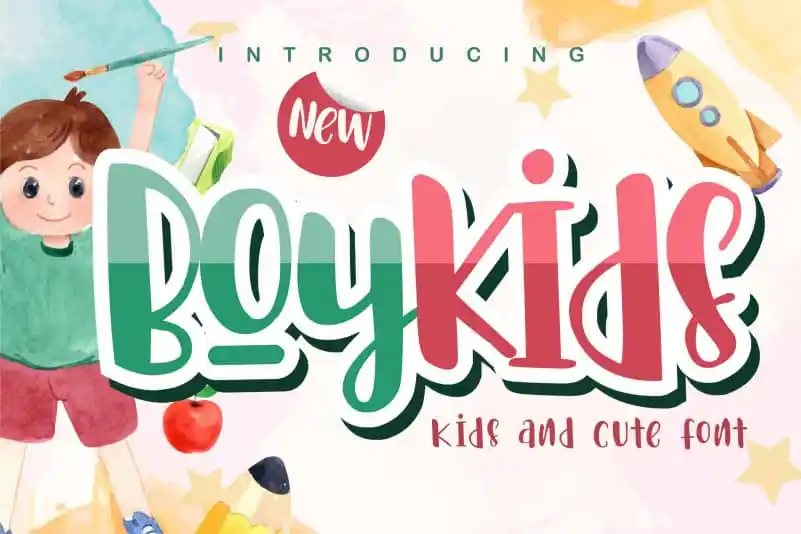
Boykids – Kids And Cute Font – Fonte Grátis
Boykids - Kids And Cute Font
A fonte ‘Boykids – Kids And Cute Font’ é perfeita para aqueles que buscam uma maneira criativa de dar vida às criações infantis e aos personagens lindamente desenhados do mundo dos animes e mangás. Com seu charme kids & cute, a fonte possui traços leves e suaves, o que torna-a ideal para criar um ambiente animado nas suas páginas web ou aplicativos, sejam eles destinados às crianças ou ao público mais jovem em geral. Ideal tanto para anúncios de produtos infantis quanto para criação de materiais educacionais, a ‘Boykids – Kids And Cute Font’ oferece uma combinação única e divertida de formas menores e traços delicados. Esta fonte é perfeita para tornar qualquer texto envolvente e encantador, transformando palavras em personagens vivos e movimentados que entretêm e atraem sua audiência, seja crianças ou jovens adultos. Adotada por criadores de conteúdo infantil, educadores digitais e designers gráficos apaixonados pela infância, esta fonte é um recurso valioso para quem busca transmitir o espírito jovial e a vivacidade da infância através do design digital.